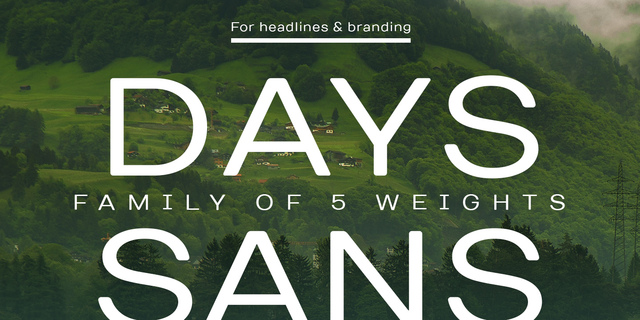
Days Sans – это прогрессивная реинкарнация легендарного бесплатного шрифта Days. В эту версию шрифта мы добавили новые начертания и поддержку многих кодовых страниц и языков. Этот шрифт отлично подходит для использования на сайтах, в мобильных и настольных приложениях. Days Sans по всем параметрам совместим со всеми шрифтами TypeType. Сфера применения: интерфейсы, инфографика, айдентика, телевидение, упаковка, выставки и презентации, образовательная литература. Шрифт разработан Иваном Гладких в студии TypeType Fonts в 2014 году.
Функции семейства TT Days SansПрименение в макете:
Ассоциации c семейством TT Days SansКачества и характер:
лаконичный, инженерный, точный, логичный, твердый, ровный, минималистичный, городской, качественный, западный, спокойный, современный, модный, комфортный, холодный, тонкий, легкий, ясный, чистый, невесомый, прозрачный, гладкий, стеклянный, хрупкий, футуристичный, проволочный, неоновый, деловой, простой, серьезный, стабильный, статичный, устойчивый, глобализированный, глобалистичный, понятный, доступный, техничный, чертежный, уверенный, надежный, спортивный, важный, убедительный, мужественный, быстрый, решительный, железнодорожный, гоночный, скоростной, мощный, сильный, авторитетный, заметный, тяжелый, индустриальный, техногенный, крутой, сексуальный
прибор, гаджет, девайс, дизайн, чертеж, чистота, гигиена, шампунь, технологии, парфюмерия, техника, инновации, наука, интернет, мобильная связь, айтишник, айти, IT, инженер, архитектура, город, конструктор, медицина, математика, коворкинг, бизнес, транспорт, аэропорт, метро, лекарство, деньги, банкнота, финансы, монета, машина, автомобиль, полиция, автобус, топливо, доставка, спорт, гонки, железная дорога, скорость, ралли, оружие, защита, тренажеры, станок, машиностроение, промышленность, энергетика, электростанция, грузоперевозки, грузовик, маталлургия, инструмент, мотор, двигатель, шоу, телевидение, авиация, компьютерная игра Стилистика:
Особенности семейства TT Days SansХит десятилетия: